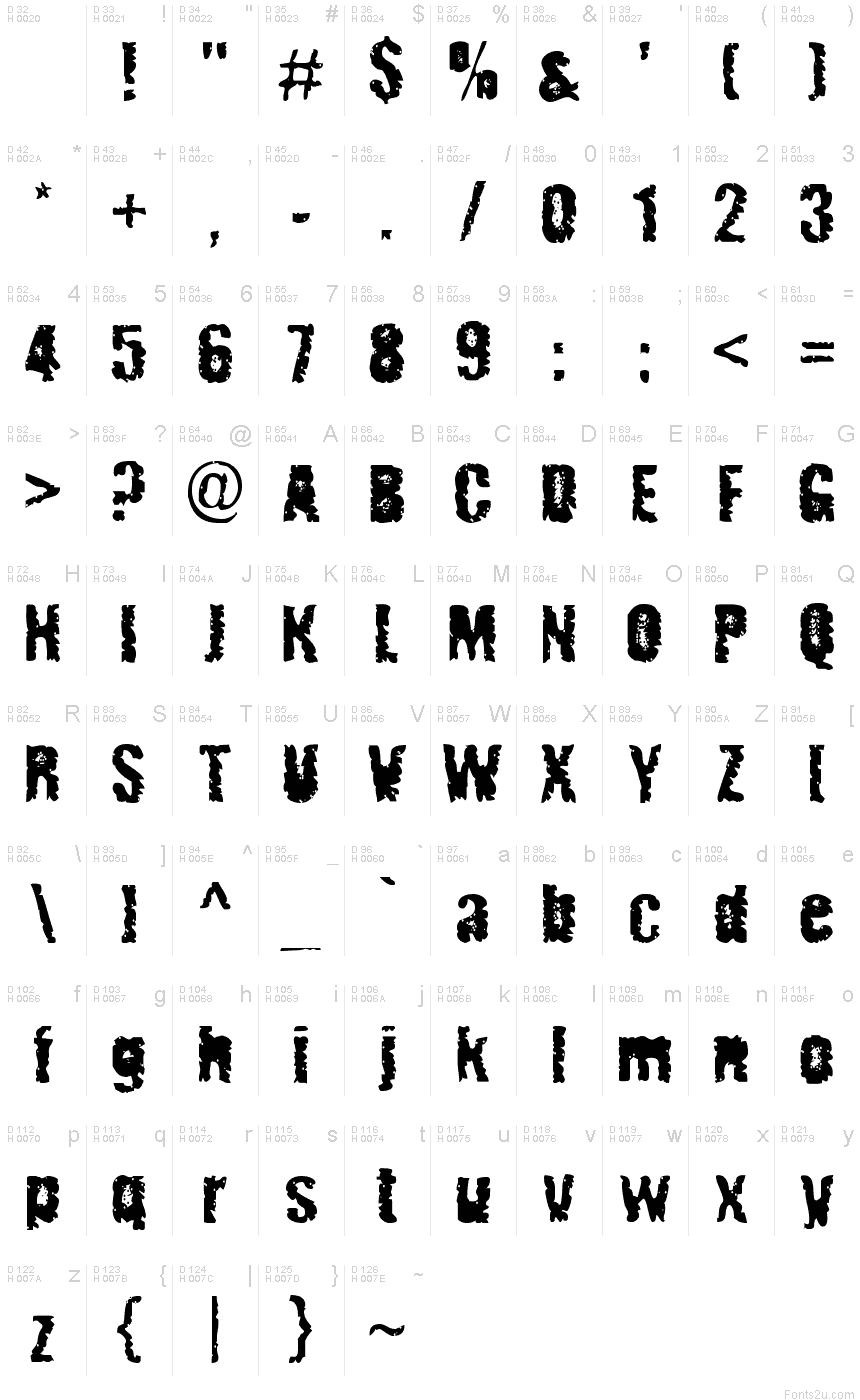
Radiated Pancake od Phillipa Andrade je bezplatné psychedelické písmo typu display s nabobtnalými, rozplývajícími se písmeny a drobnými kráterovitými výřezy. Celá abeceda díky tomu působí jako rozžvýkaná, rozteklá a lehce radioaktivní. Těžké černé tvary odkazují na estetiku plakátů z konce 60. let, kde se každá křivka vydouvá ven a drsná vnitřní textura brání tomu, aby znaky působily příliš uhlazeně.
Toto bezplatné písmo se hodí na hudební letáky, skate grafiku, obálky zinů, festivalové plakáty a výrazné obaly, kde písmo může fungovat spíše jako obraz než jako neutrální nadpis. Hodí se také pro krátké titulky, kartičky s názvy a logotypy, protože masivní siluety a vysekaná textura dodávají i krátkému slovu zvláštní, rosolovitý tep.